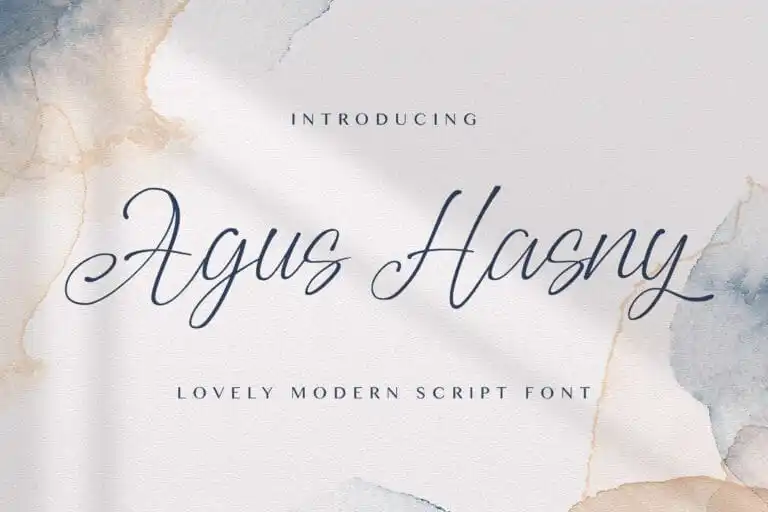
A Agus Hasny Calligraphy Font é uma opção incrivelmente suave para qualquer designer que busca adicionar um toque único e moderno aos seus projetos digitais. Este tipo de escrita artesanal mantém a classificação clássica da tipografia churrascaria enquanto se destaca com seu movimento dinâmico em pressão. Essa fonte é perfeita para quem busca transmitir um estilo elegante e criativo em seus trabalhos, seja uma revista especializada ou até mesmo um site pessoal moderno. Perfeito tanto para aqueles que valorizam a tradição do churrasco da escrita quanto para designers que adoram experimentar novos estilos de forma atual, a Agus Hasny Calligraphy Font é um verdadeiro consolador para criadores de conteúdo e designers de interface. Sem dúvida, ela pode transformar qualquer projeto em algo realmente especial, elevando-o ao próximo nível. Acesse agora e descubra o seu potencial!